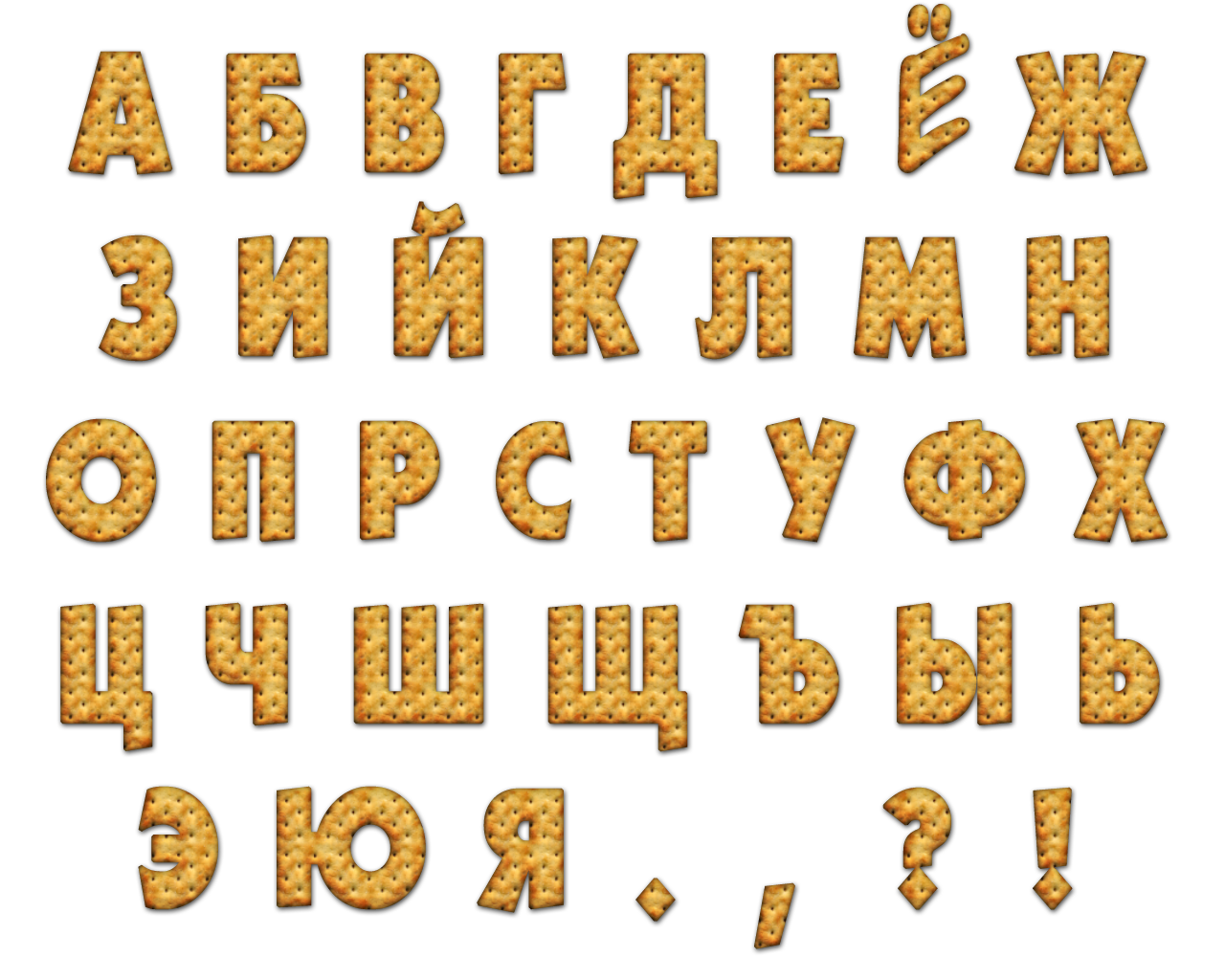
Секреты красивых надписей на страничках уроков фотошопа для начинающих.
Как быстро выбрать шрифт.
В уроке показано как быстро выбрать текст из списка шрифтов, загруженных на Вашем компьютере.Рельефный текст.
Рельефный текст можно использовать для вашего баннера или сайта.
Оригинальная надпись всегда привлекает внимание.
Объемный текст.
Нашла интересный урок по превращению обычного текста в объемный.
Сделаем в уроке текст, буквы которого будут словно вырезаны из центра.
Заполнение крупного плакатного шрифта изображением.
Возможно Вам встречались плакаты с очень крупным шрифтом, который был заполнен рисунком или интересной текстурой.
Сделаем в уроке текст, буквы которого будут словно вырезаны из картинки.
Как написать текст по кругу.
Текст можно написать не только по кругу, но и по любой кривой линии, которая обязательно должна быть контуром.
Проверим на практике, как написать текст по контуру.
Как написать текст на кружке.
Захотелось отправить открытку с пожеланиями «Доброе утро» своим друзьям в «Одноклассниках». Текст решила написать на кружке.
Как написать текст по кругу можно узнать из урока написанного ранее.В данном примере текст надо деформировать по цилиндрической поверхности.
Как написать хромированный текст.
Применяем к слою с растрированным текстом эффект тиснения. Параметры в уроке показаны на скриншоте.Применяем корректирующий слой «Цветовой тон — Насыщенность» и добавляем цвет чтобы получить эффект блестящего хромированного текста.
Коллекция русских шрифтов.
Секрет красивых надписей
заключается еще и в выборе подходящего шрифта.
В работе чаще всего используется не более десятка любимых шрифтов для эффектных надписей. Вашему вниманию предлагается небольшая коллекция русских шрифтов с образцами их использования. На этой страничке сайта adobemaster.ru Вы можете скачать русские шрифты бесплатно.
Коллекция каллиграфических русских шрифтов.
Шрифт «Ласточка» сделает Вашу надпись каллиграфической. Он тонкий и изящный. Русский шрифт в стиле небрежной каллиграфии будет хорош для поздравительных открыток.
Коллекция русских декоративных шрифтов.
Фото бывают разными и поэтому текст на фото приходится делать разными шрифтами. Красивые декоративные русские шрифты хорошо дополнить обводкой и выделить тенью.
Русский шрифт «Габриола» послужит
декоративным украшением.
Стеклянный текст.
Среди многочисленных уроков по фотошопу нашла несколько вариантов создания стеклянного или прозрачного текста.
Самый сложный вариант — применение команды Layer > Create Clipping Mask (Слой > Создать обтравочную маску).
Секреты красивых надписей.
Надписи на поздравительных открытках имениннику или юбиляру должны быть выразительными и интересными. Просто выбором оригинального шрифта здесь не обойтись. Только различные стили и эффекты, примененные к тексту, позволят нам красиво оформить поздравление.
50+ лучших шрифтов мелом для фотошопа (+кириллица)
В данной статье сможете бесплатно скачать шрифты мела для фотошопа, которые пригодятся вам в разных дизайнерских решениях на сайтах, иллюстрациях, приложениях или даже в офлайне (например, иногда владельцы кафе оформляют меню в этом стиле).
Подобный вариант с декоративным шрифтом надписи мелом также неплохо будет смотреться в полиграфии. Где бы вы его не применили, подборка ниже окажется полезной. Всего собрали около 50-ти объектов на любой вкус.
Перед тем, как перейти к рассмотрению материалов, хочется заметить, что некоторые из них изначально (в превью) могут не вызывать ощущения шрифта мела на доске. Однако если вы в качестве фона добавите подходящую текстуру, то имитацию надписи, практически невозможно будет отличить от настоящей.
Как видите, вариантов реализации текста великое множество, в частности вы смело можете использовать разные цвета для него, не обязательно белый. По стилистике решения тоже слегка отличаются — есть рукописные, жирные, строчные, заштрихованные буквы и т.п. Однако при правильной комбинации фона и шрифта мела для фотошопа сразу возникает ощущение того, что надпись сделана именно мелом, а не чем — то другим. Таков эффект его применения и восприятия. Возникающие у большинства ассоциации со школьной доской, в принципе, логичны.
DK Crayon Crumble
Rayando
FFF Tusj
Syphon Spritz
Grutch Shaded
pencilPete
Hesster Moffett
Eraser
Chalk Line
Conte Script
PWDolphins
vtks noise
Colored Crayons
Coffee House
Denne Milk Tea
Используйте эти фонты для создания различных стилизованных текстов. Они пригодятся для оформления сайтов, праздничных надписей, открыток, баннеров или плакатов. Все зависит от воплощения ваших творческих фантазий.
Black Crayon
DJ Gross
PWScritch
Orange Juice
Vtks Love Love
Vintage One